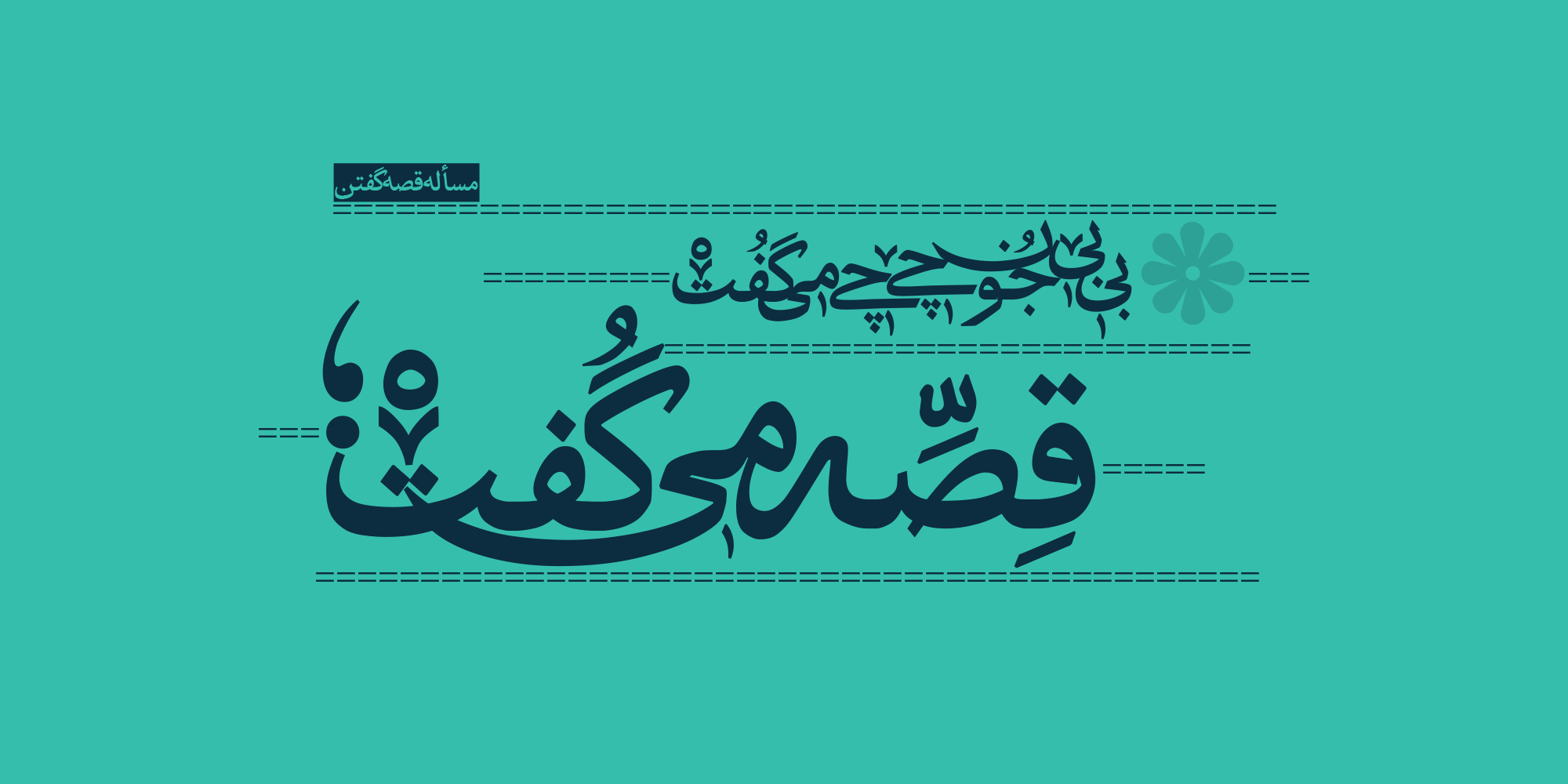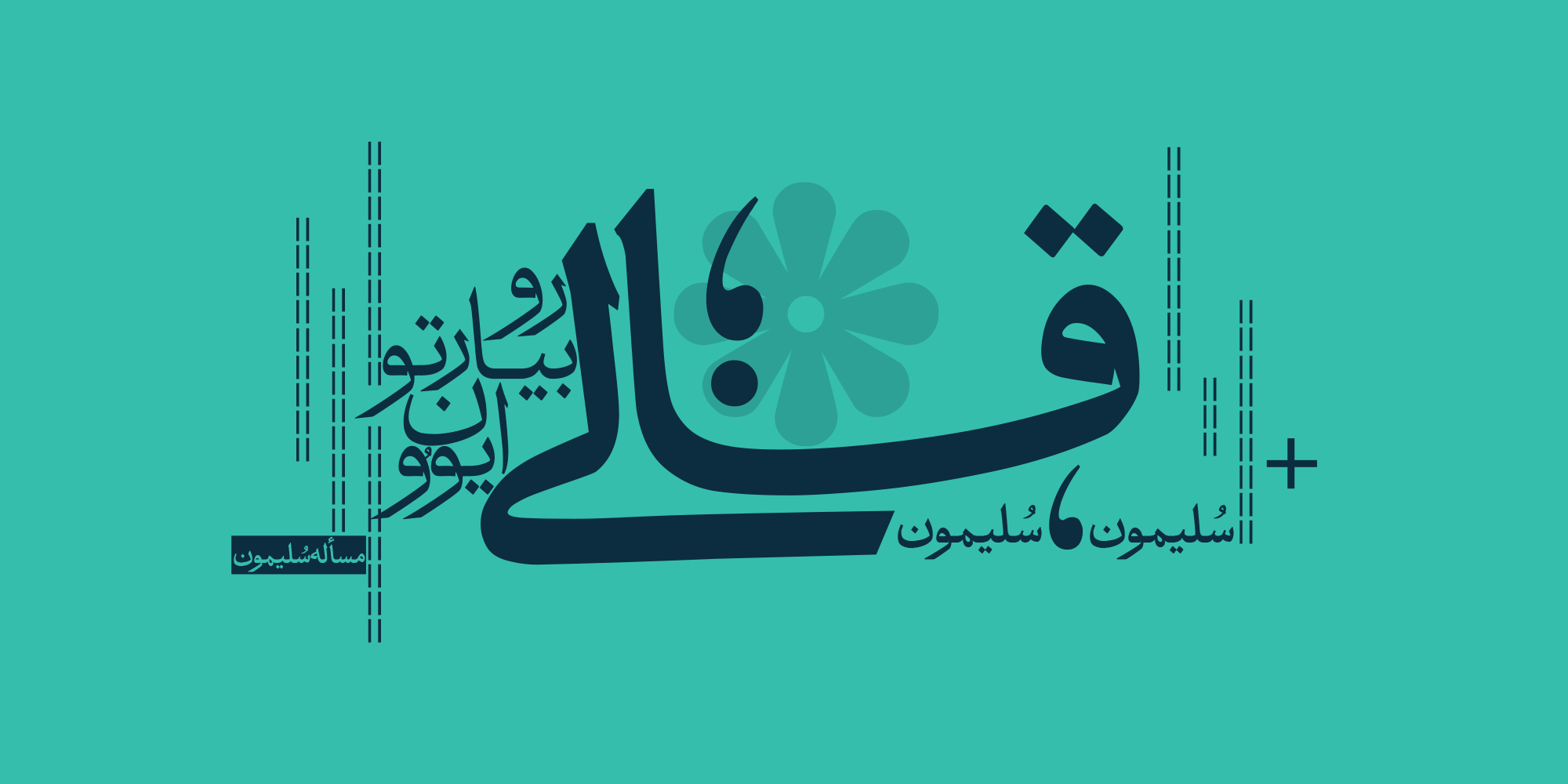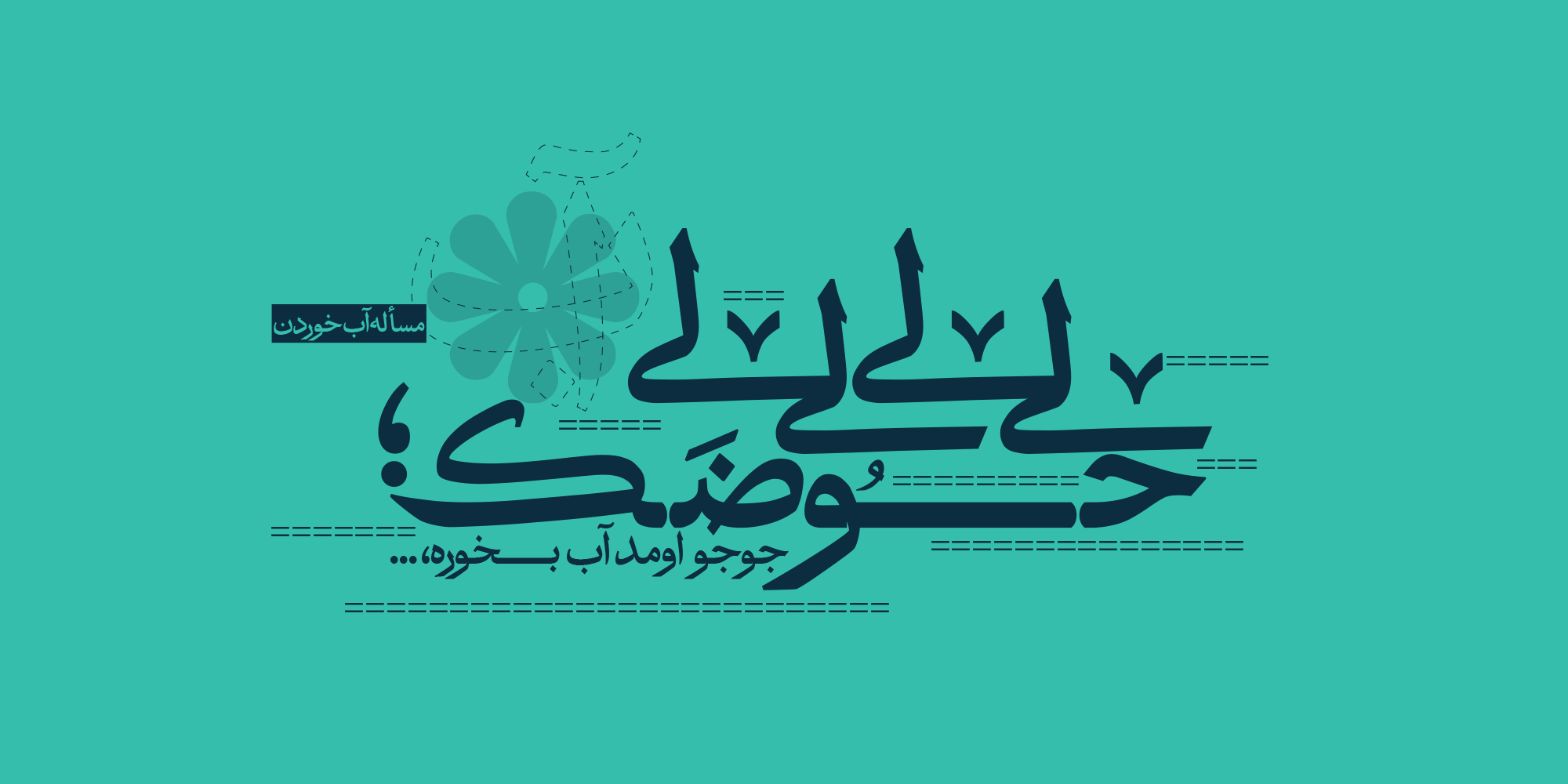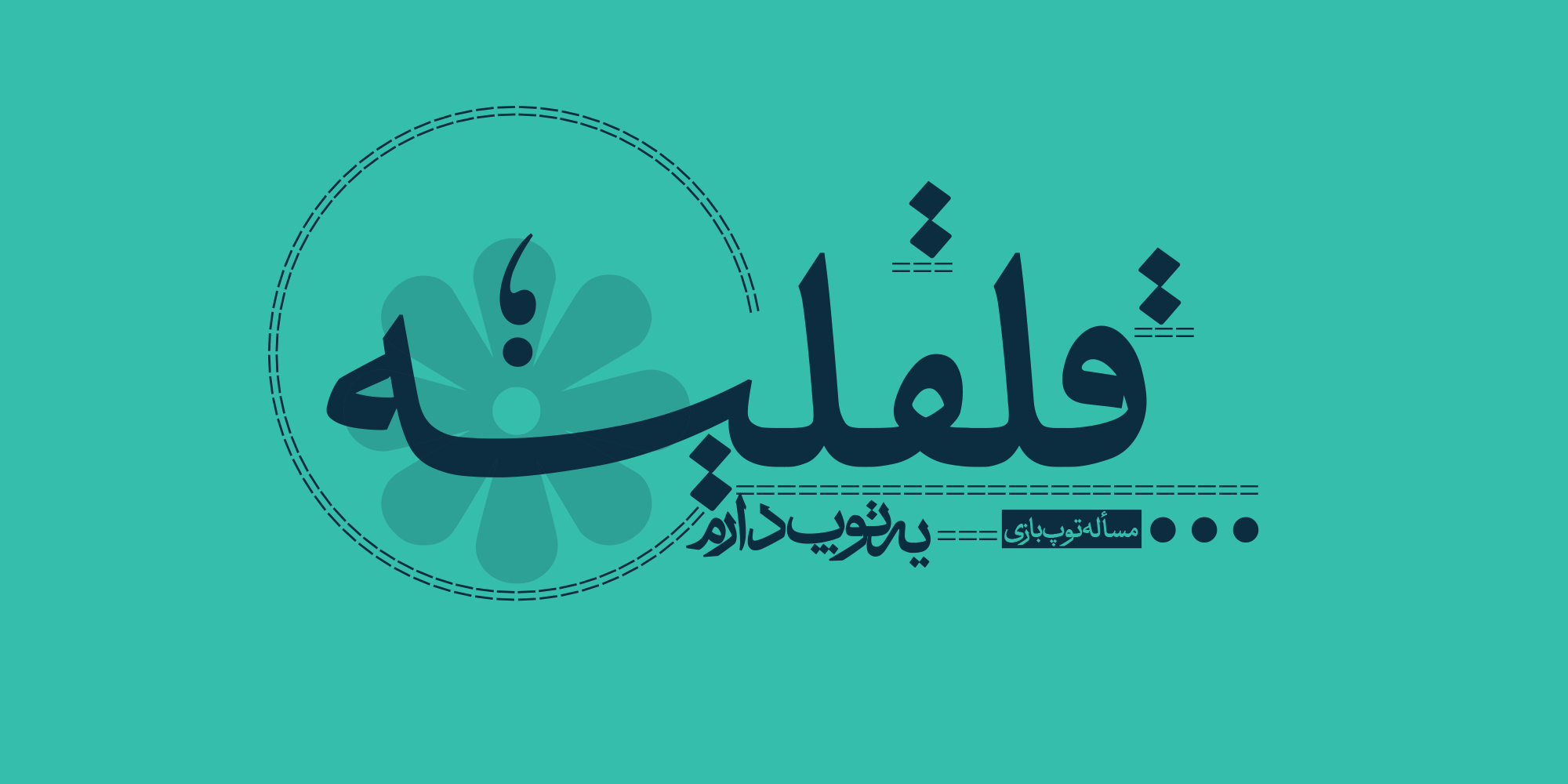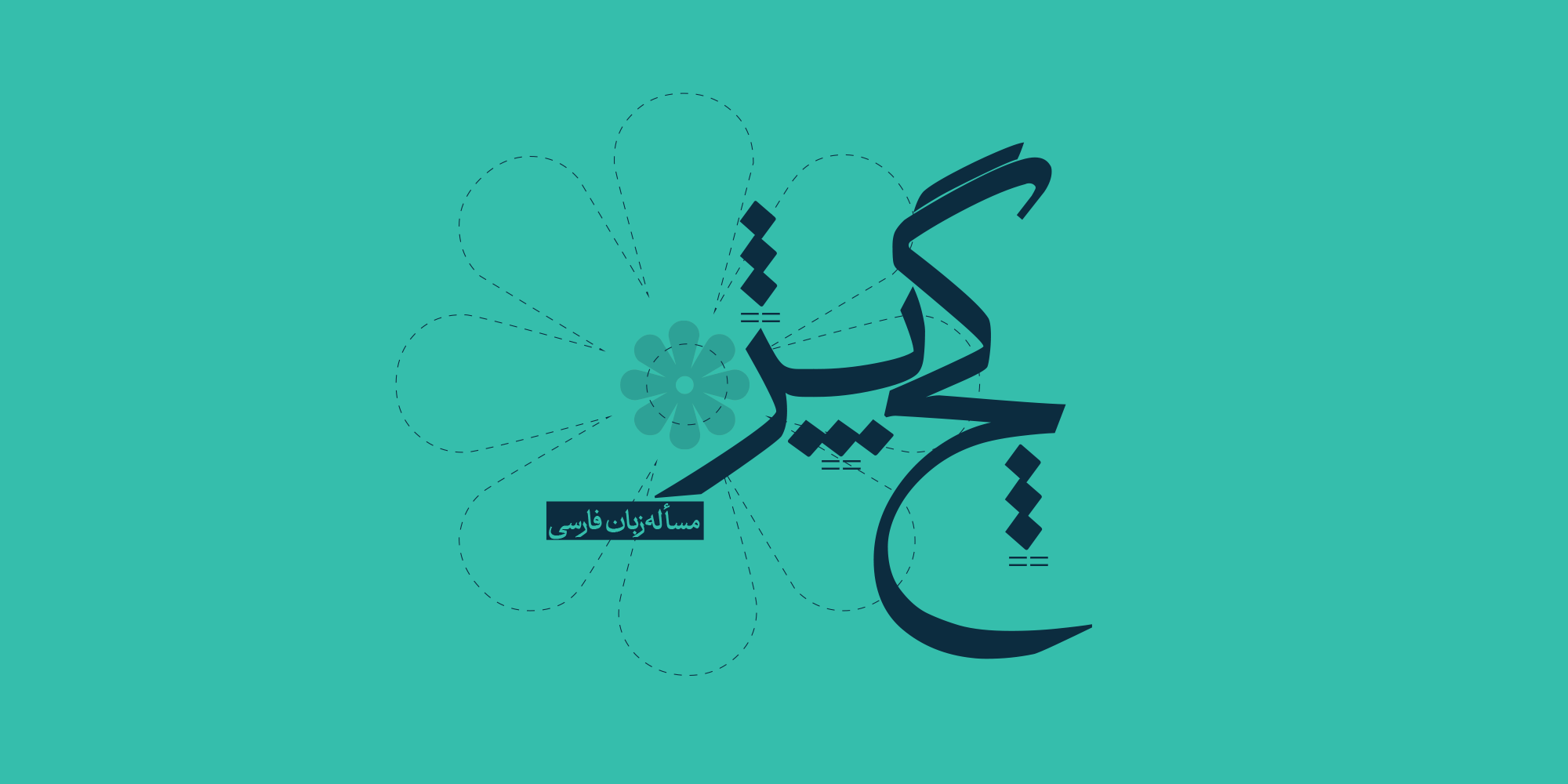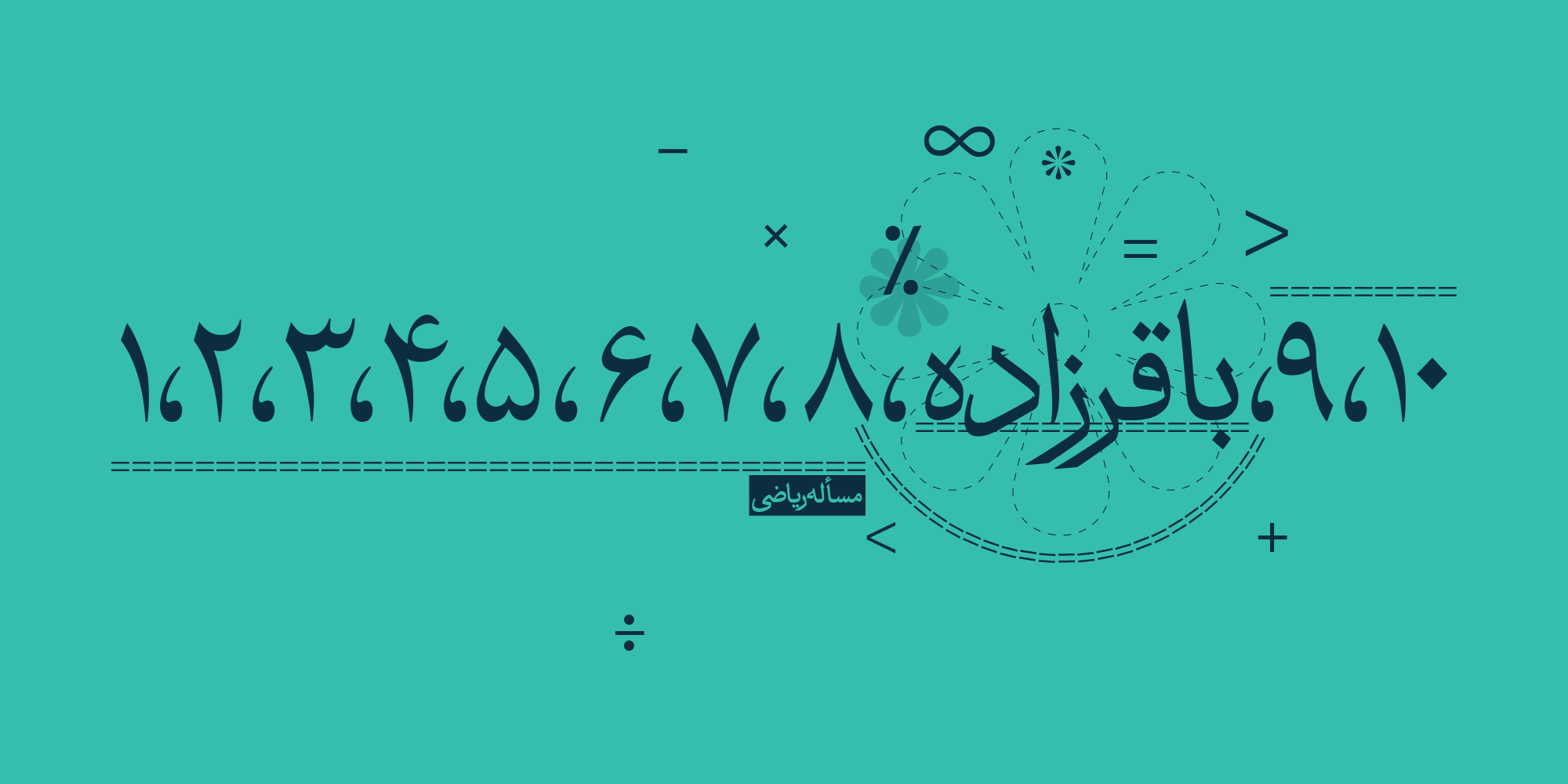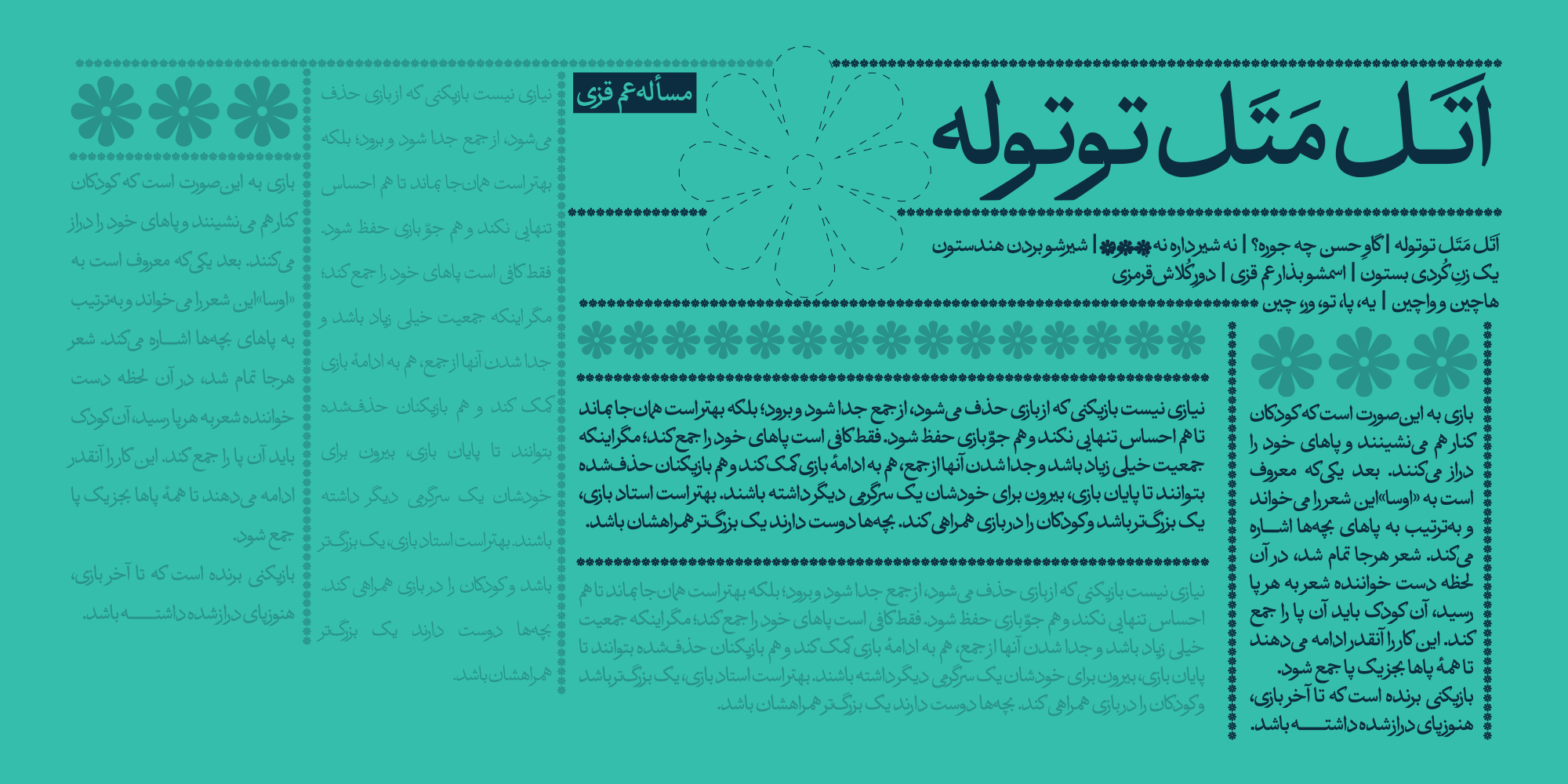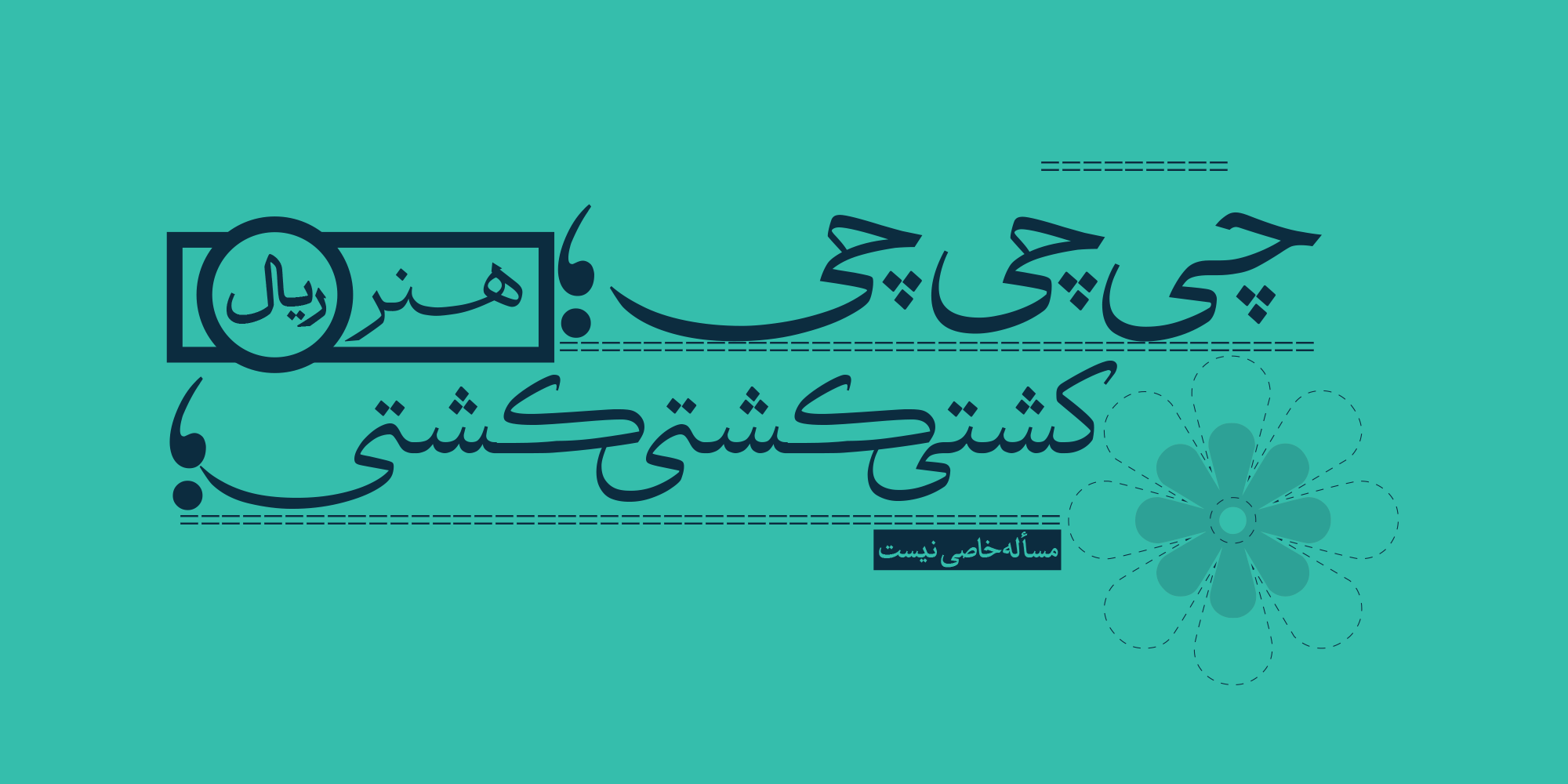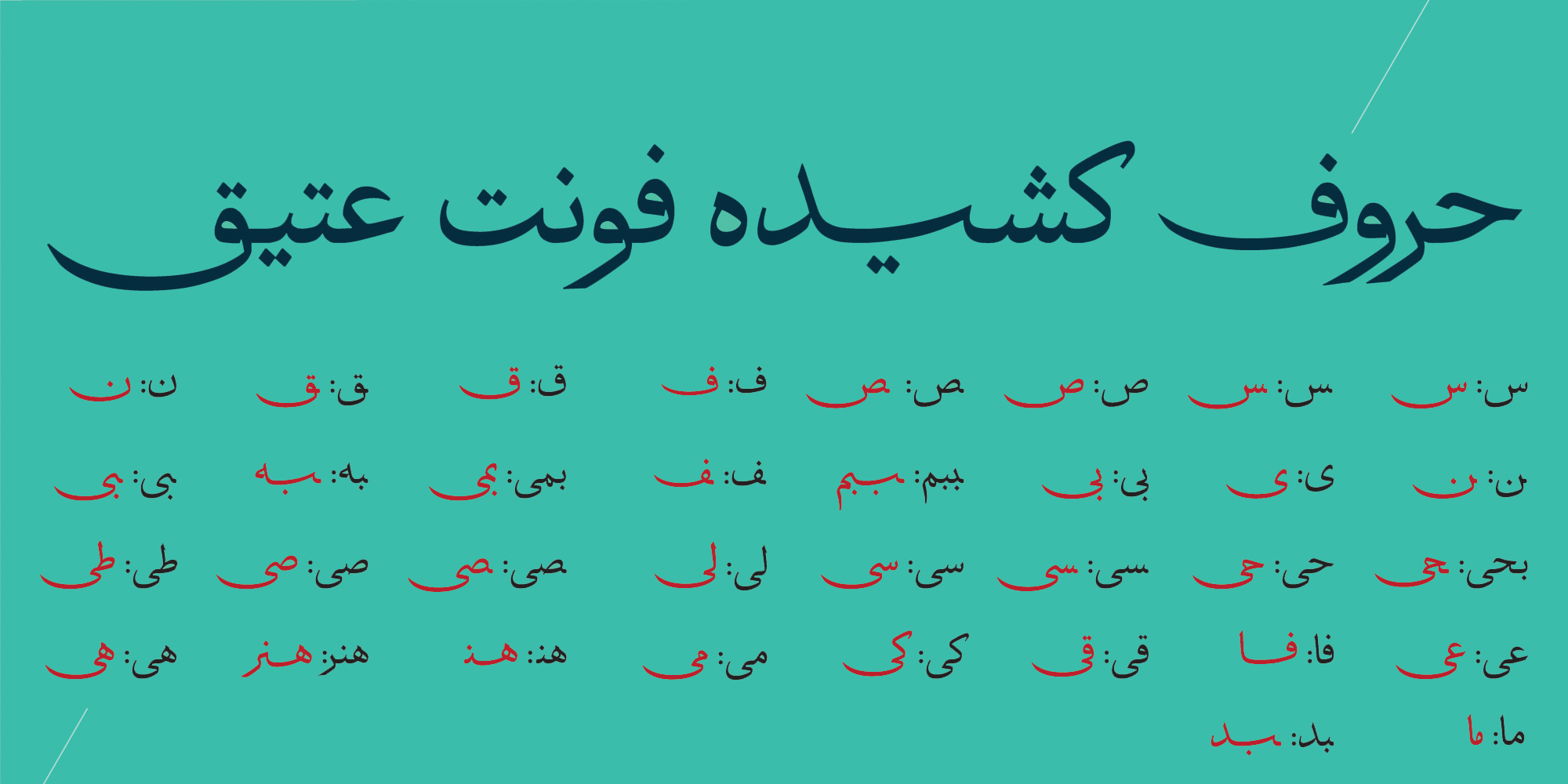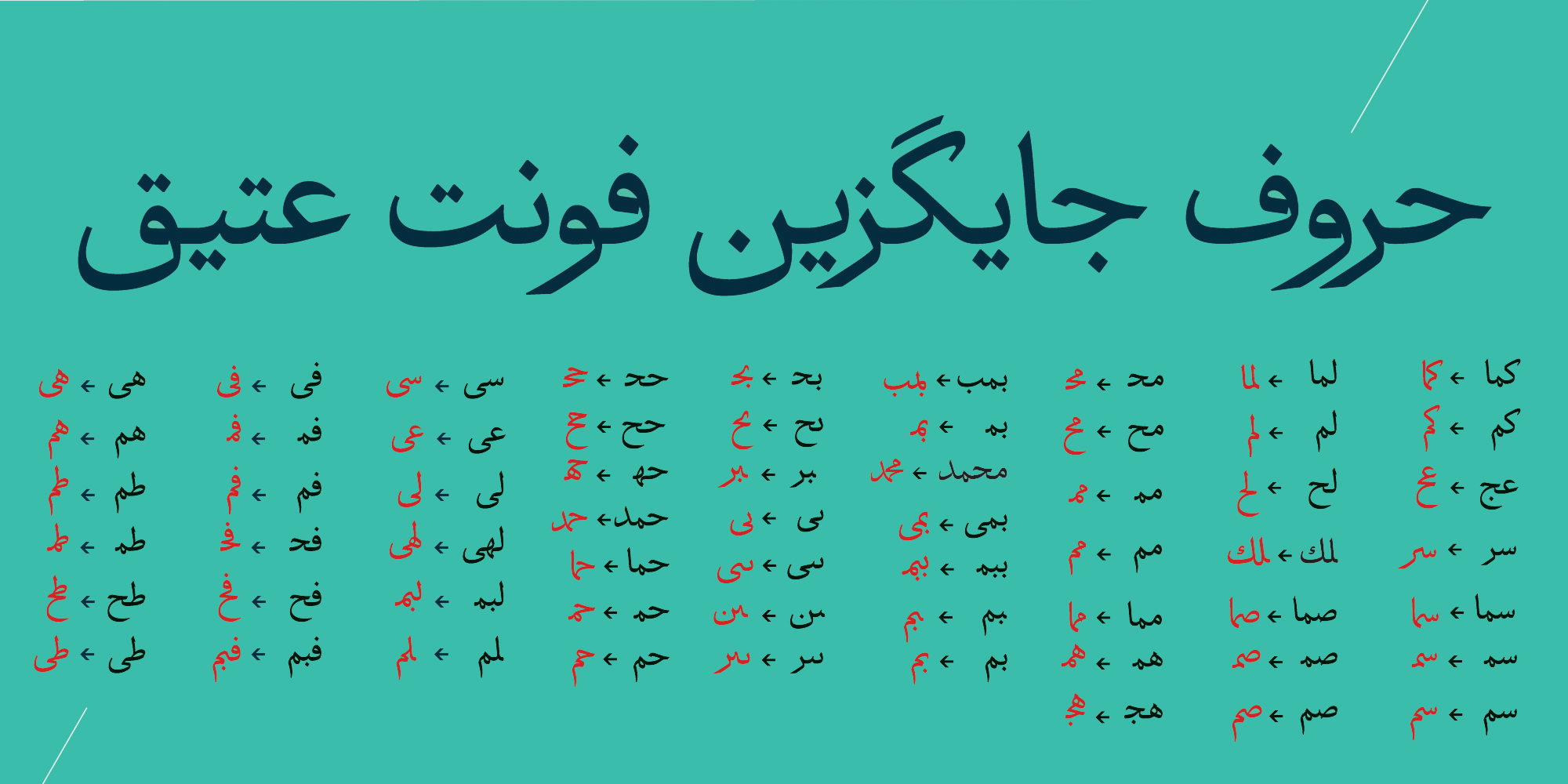
فونت عتیق شخصیتی سیال و نوستالژیک دارد. این فونت در دهه 20 خورشیدی در روزنامههای ایران راه یافت و تا سالهای اغازین دهه 40 ادامه یافت.
در دیزاین این فونت تلاش براین بوده تا اشکالات فنی و زیباییشناختی فونت برطرف شود و لیگیچرهای مناسب و جدید برای آن طراحی شود. برای بسیاری از حروف، گلیفهای جایگزین طراحی شده است، این قابلیتها به شما قدرت انتخاب و ایجاد تنوع در تایپوگرافی را میدهد.
فونت عتیق دارای ۸۷۰ لیگچر و حروف کشیده جایگزین است. برای استفاده از این ویژگیها به راهنمای فونت مراجعه کنید:
فونت عتیق دارای سه وزن است. نازک. میانه و ضخیم.
فونت عتیق در استفاده: